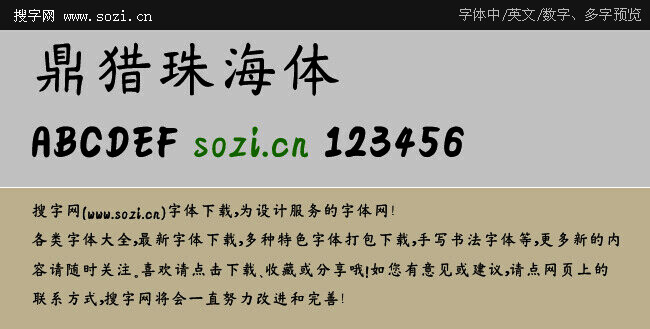
鼎獵珠海體
搜字網提供一款鼎獵珠海體中文藝術字體下載,鼎獵珠海體以珠海先賢蘇曼殊墨寶,“金玉良言常佩帶,芝蘭濃馥振精神。”為緣起。是一套融入了珠海特質的字體。共計設計了7905個字符,其中漢字6916個。在6763個漢字基礎上,特別增加了153個常用粵語漢字,可以滿足絕大部分印刷設計等要求。這套字體面向全社會(包括企業商用)永久免費開放使用。但禁止用于任何違法違規用途。字體適合海報設計、廣告創意、包裝設計等應用。